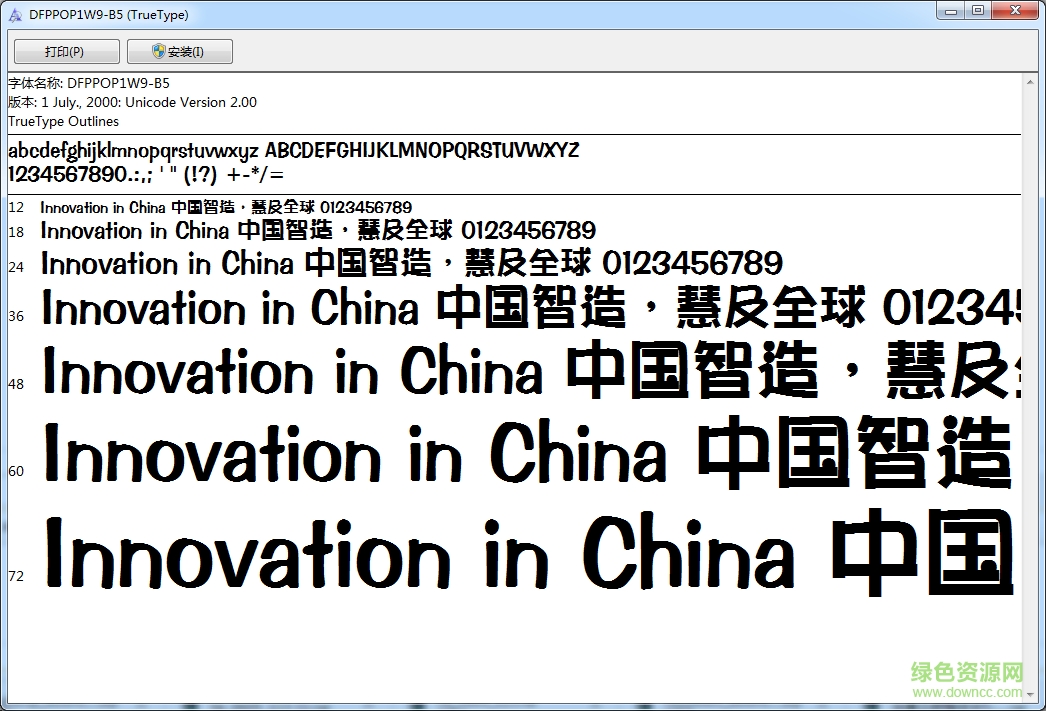
dfpop1w9常規(guī)日語(yǔ)字體
dfpop1-w9字體是一款充滿個(gè)性的華康pop1字體,字形飽滿,布白均勻,剛中帶柔,整體氣質(zhì)活潑大方,適合用在海報(bào)設(shè)計(jì)中,需要的朋友快來(lái)綠色資源網(wǎng)下載吧!
dfpop1w9字體特點(diǎn)
POP體擁有手繪般的美工字體風(fēng)格,勻稱飽滿的筆劃,模仿了麥克筆的設(shè)計(jì)感,俏皮的點(diǎn)筆、連筆,使字體本身極具親切感,拉近傳遞訊息的距離。相當(dāng)適合用于各種場(chǎng)合的宣傳海報(bào)、標(biāo)題用字